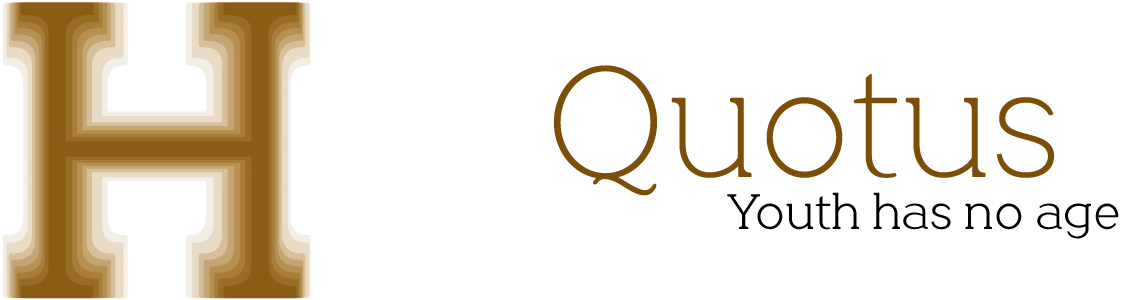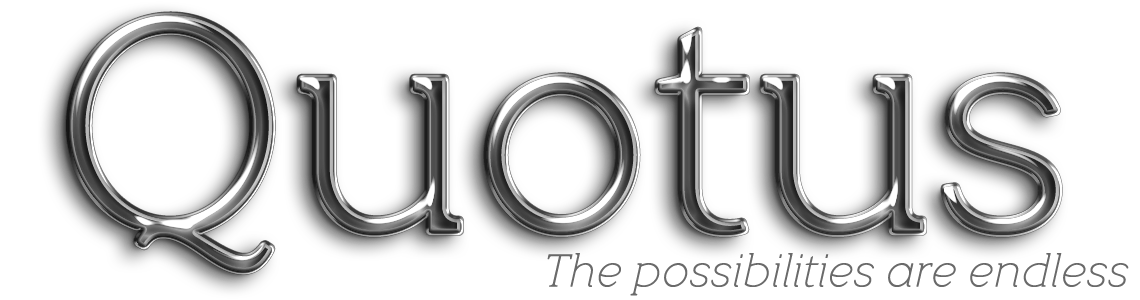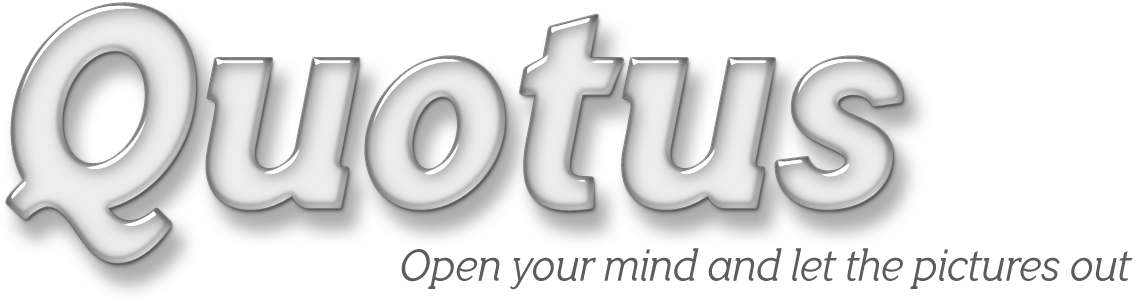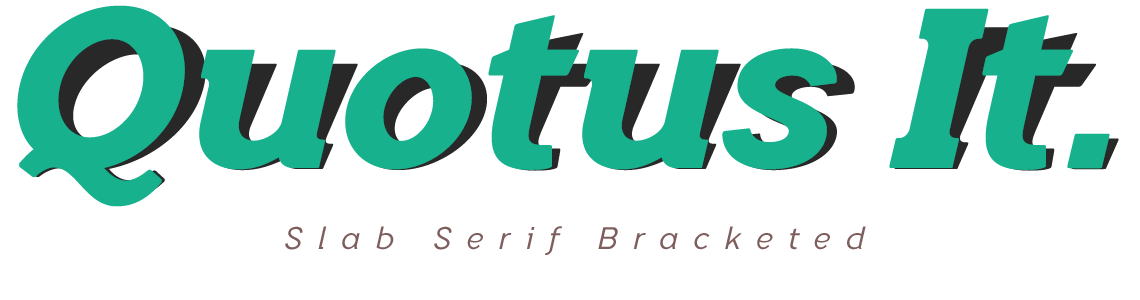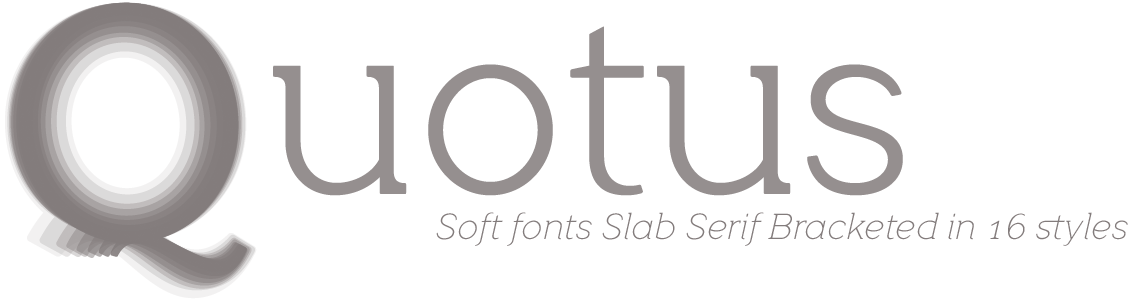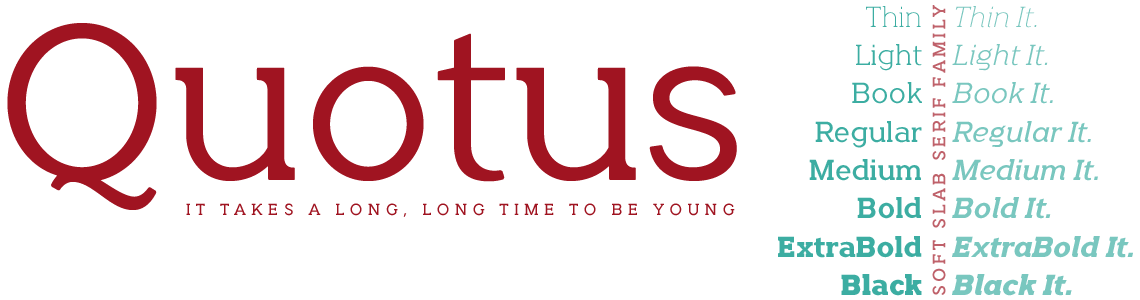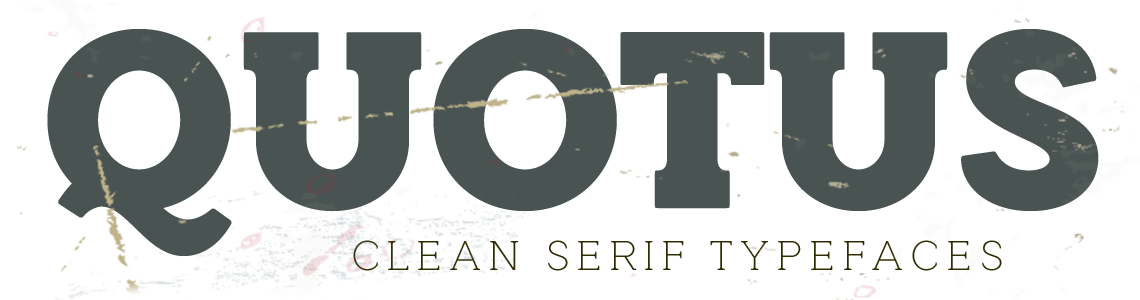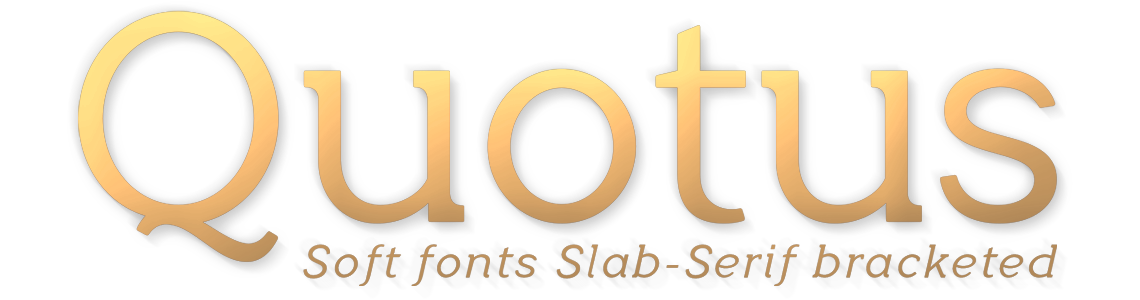
Slab Serif Fonts
Estilo: Slab Serif Bracketed, Geométrica, Corporativa
Proporción: Thin, Light, Book, Regular, Medium, Bold, ExtraBold & Black + Italics
En el desarrollo de estas fuentes he definido cuidadosamente la anchura de cada letra y la anchura de las astas verticales y horizontales así como las métricas y el Kerning para conseguir un juego de letras equilibrado de la máxima legibilidad en cualquier tamaño y para multitud de usos en diseño gráfico, editorial, packaging, señalización, etc. cubriendo todas las necesidades de escritura que requiere cualquier proyecto corporativo o publicitario.